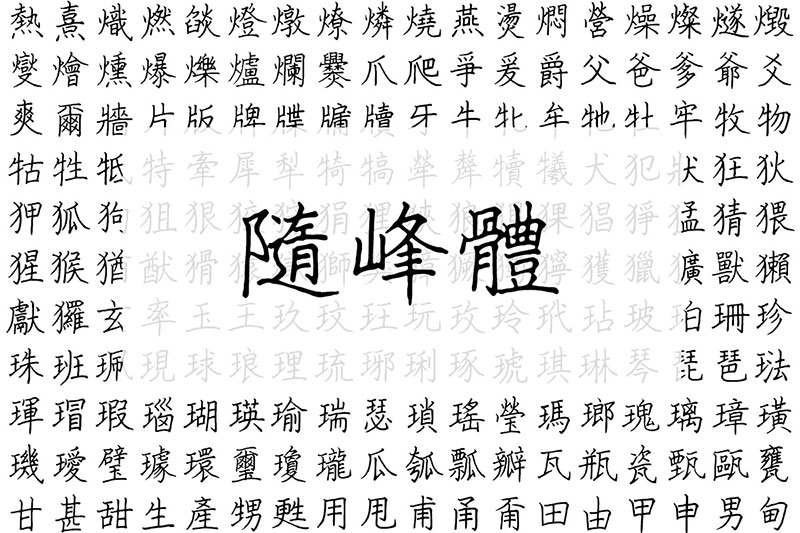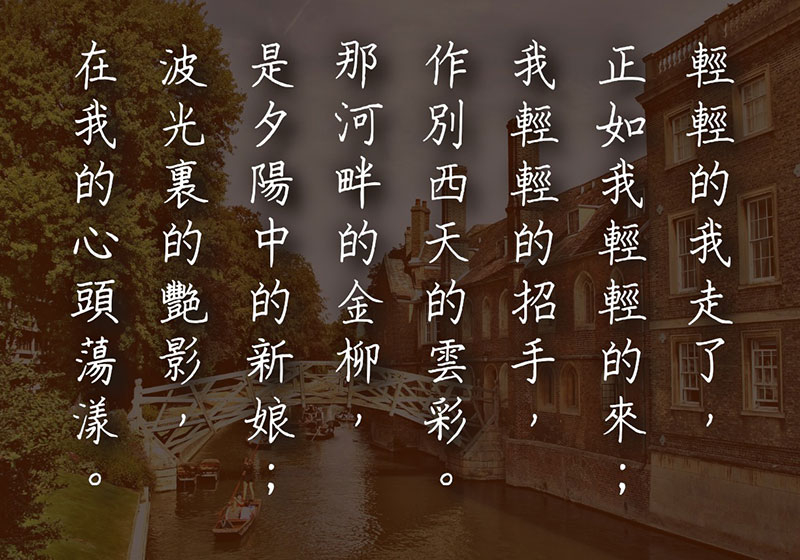
“隨峰體”的創作者是阿坤,一位熱愛寫字的香港人。“隨峰體”是經過兩年時間,逐字逐字以啫喱筆寫成的手寫字體,而且保留手寫痕跡和瑕疵。早在一年前就決定以開源形式釋出字體,完全免費,可以自由商用,希望大家喜歡。Beta版推出之後,會根據用家意見不斷完善字體,以及統一字體風格後,再同樣以開源形式推出正式版,敬請期待!